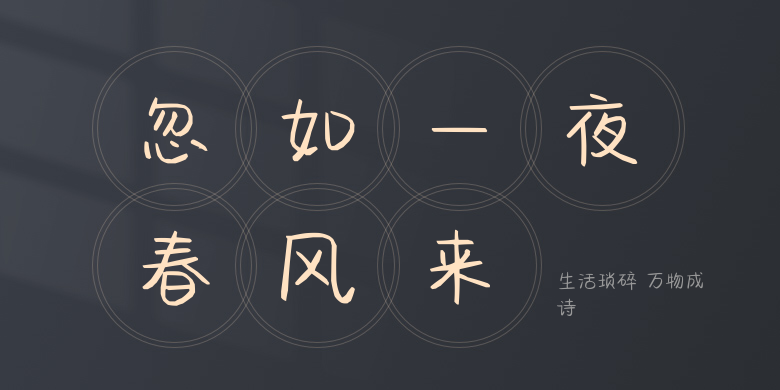
生活琐碎 万物成诗
生活琐碎 万物成诗,这款字体结构工整、笔画清晰,兼顾美观与易读性,适用于标题、正文、海报、包装、LOGO 等多种场景。字形优雅稳定,风格百搭耐看,适配日常排版与创意设计,让文字呈现更舒适、更具质感。生活琐碎 万物成诗一笔一画,皆是细节,以均衡的比例、流畅的线条打造舒适视觉体验,字形端正大气,风格简约现代。无论是商业设计、品牌宣传还是日常排版,都能轻松驾驭,让文字更有格调与力量。生活琐碎 万物成诗字体下载。